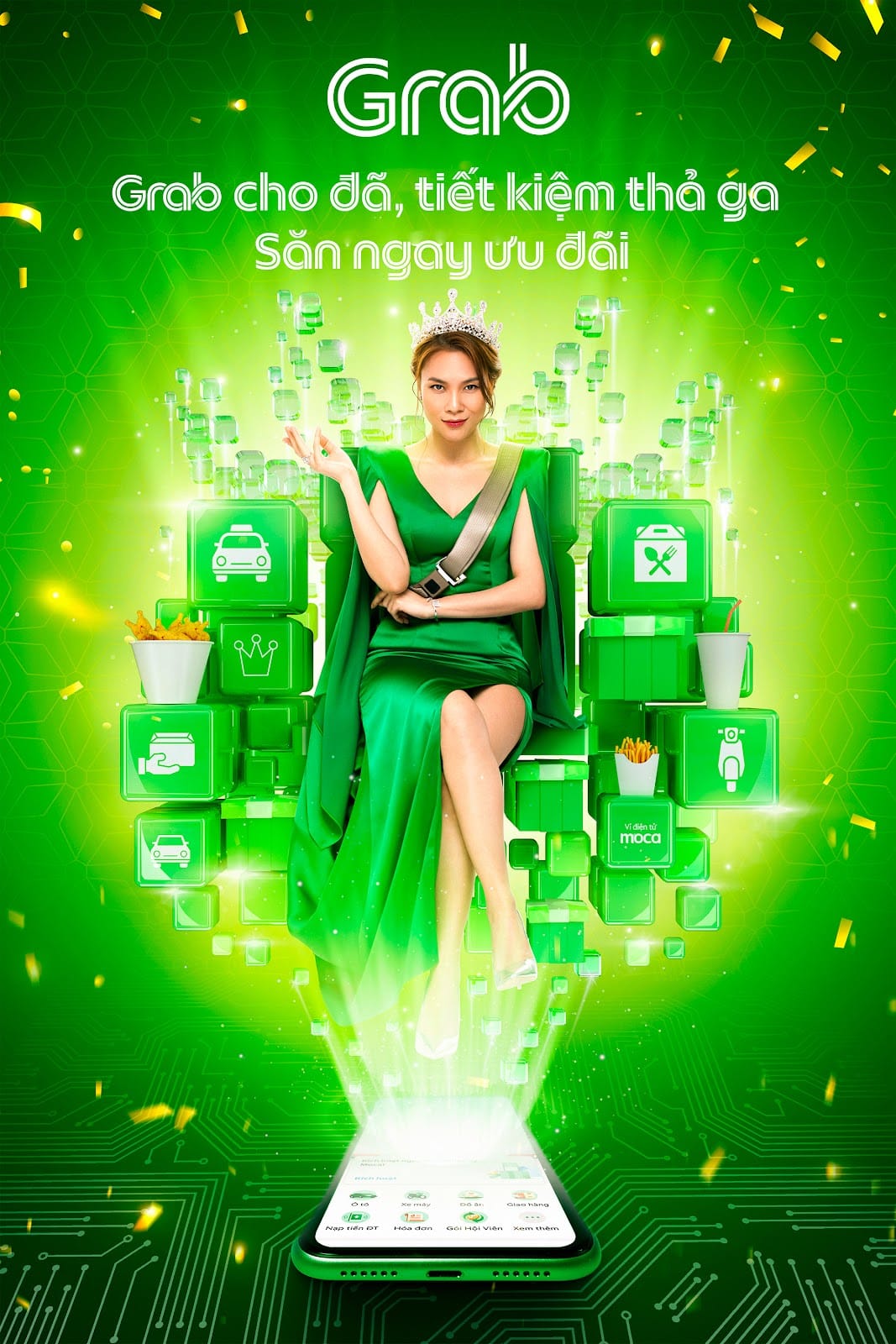
Mỗi thương hiệu đều có bộ nhận dạng thương hiệu riêng, tương tự như thì Grab cũng có một font được thiết kế riêng khá ấn tượng. Với 2 đường nét tách rời giống như vạch kẻ đường vậy.
Font Grab có hỗ trợ gõ Tiếng Việt đầy đủ. Ngoài ra, mình thấy font này chỉ phù hợp với các văn bản ngắn và size chữ to thì mới đẹp, không phù hợp với các văn bản dài cho lắm vì rất khó nhìn và khó đọc.